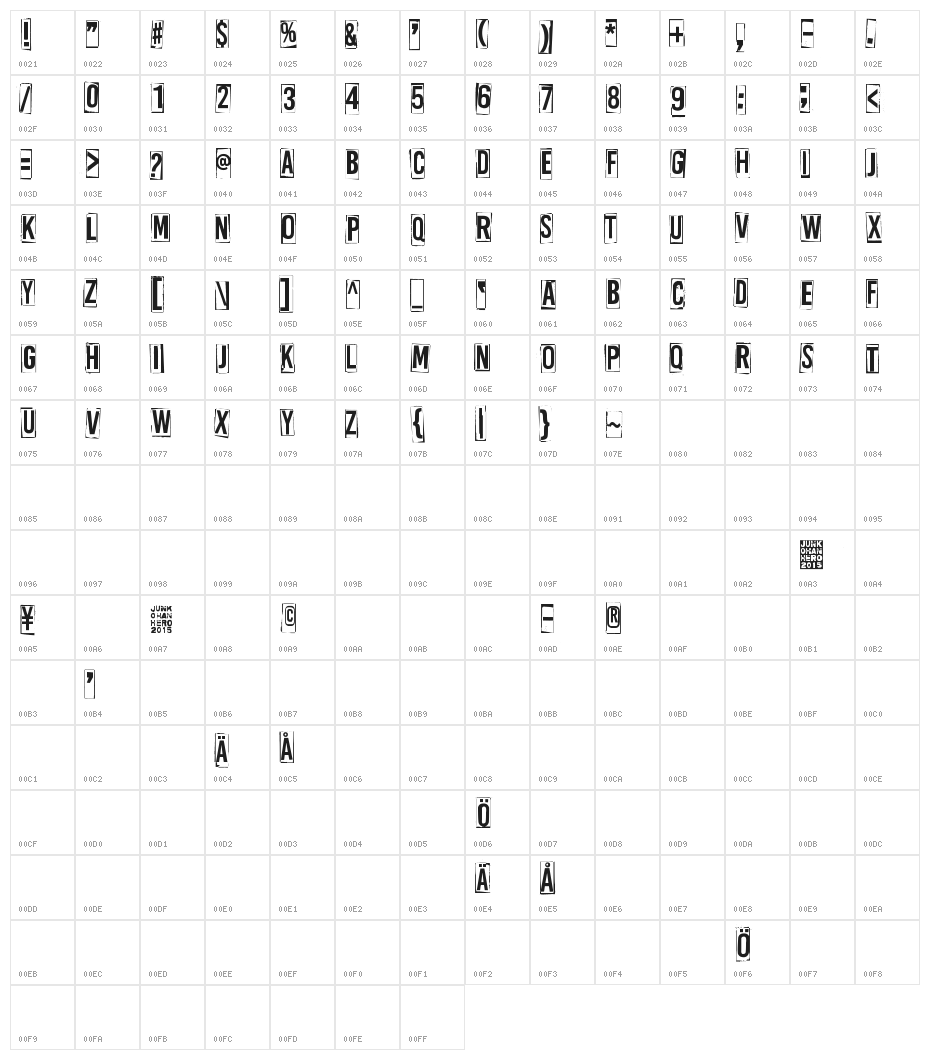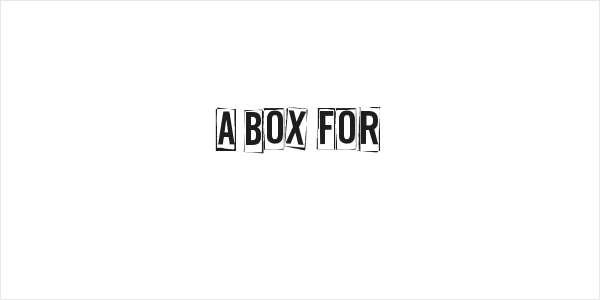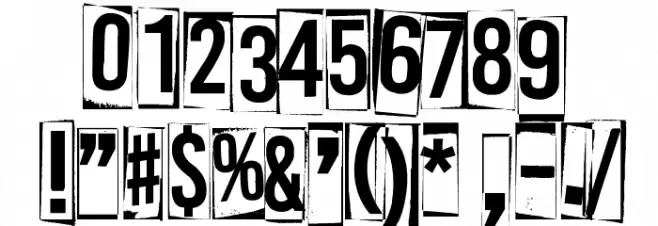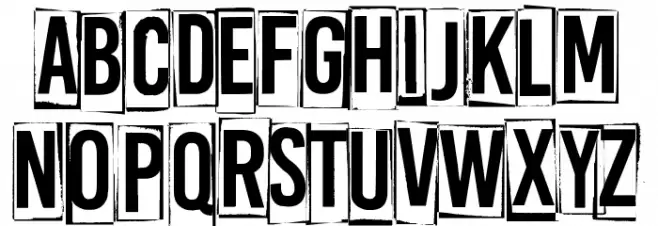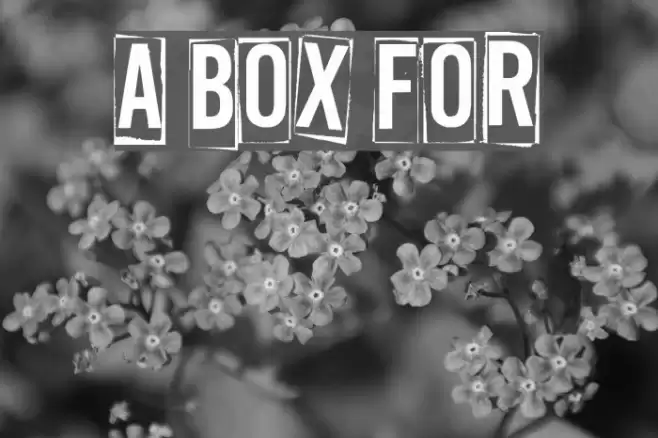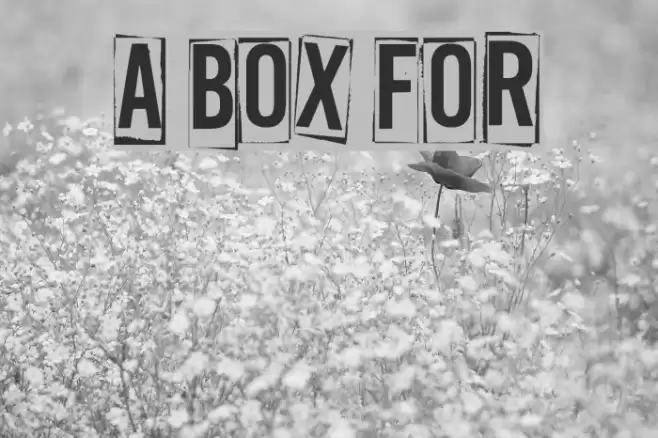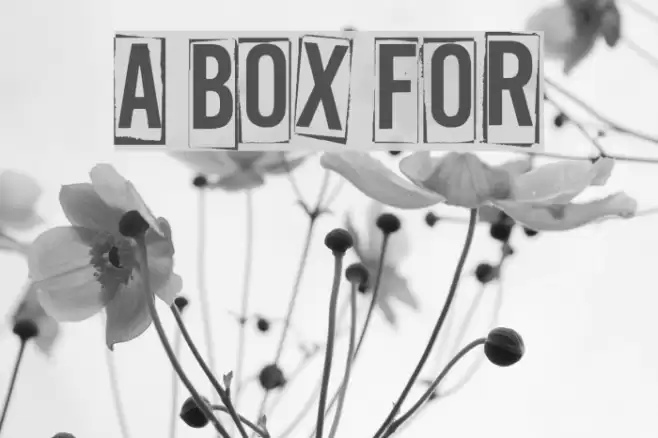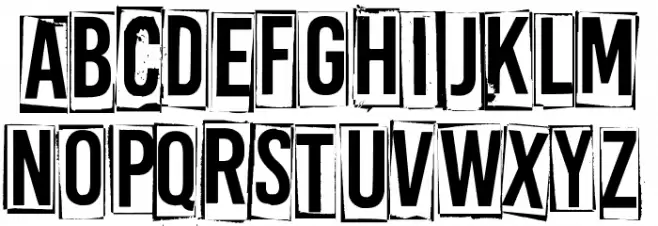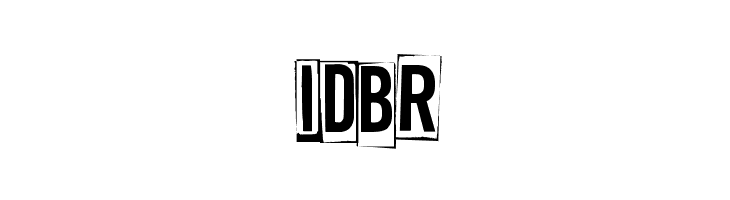
A Box For Font
✎ Distorted Eroded
| श्रेणियाँ | Distorted Eroded |
| समग्र शैली | Vintage |
| उपयोग का मामला | Headlines, Logos, Posters |
| सुझाए गए प्रोजेक्ट | Ideal for posters, album covers, branding for edgy or vintage-themed products, and any design needing a bold, impactful statement. |